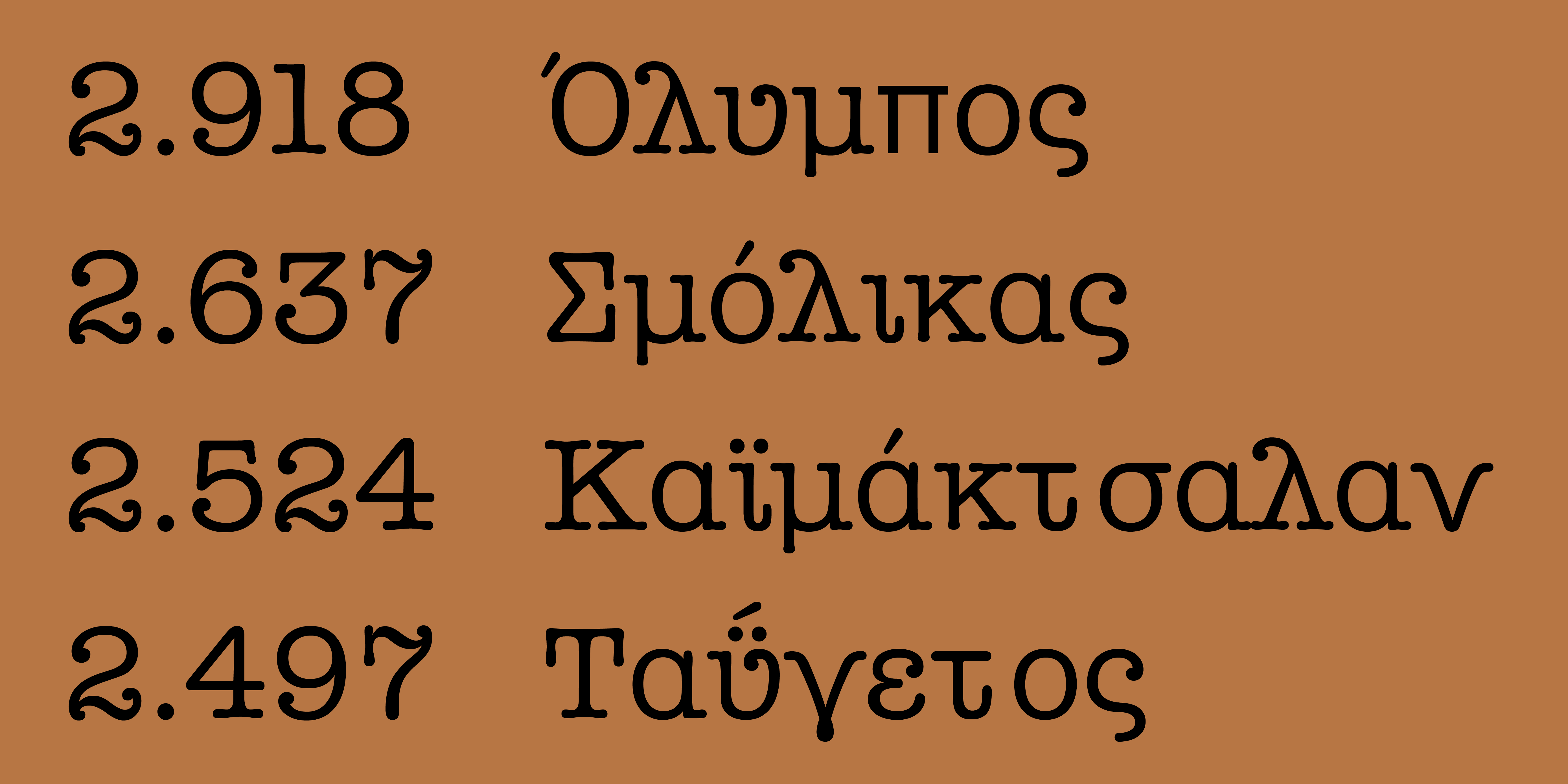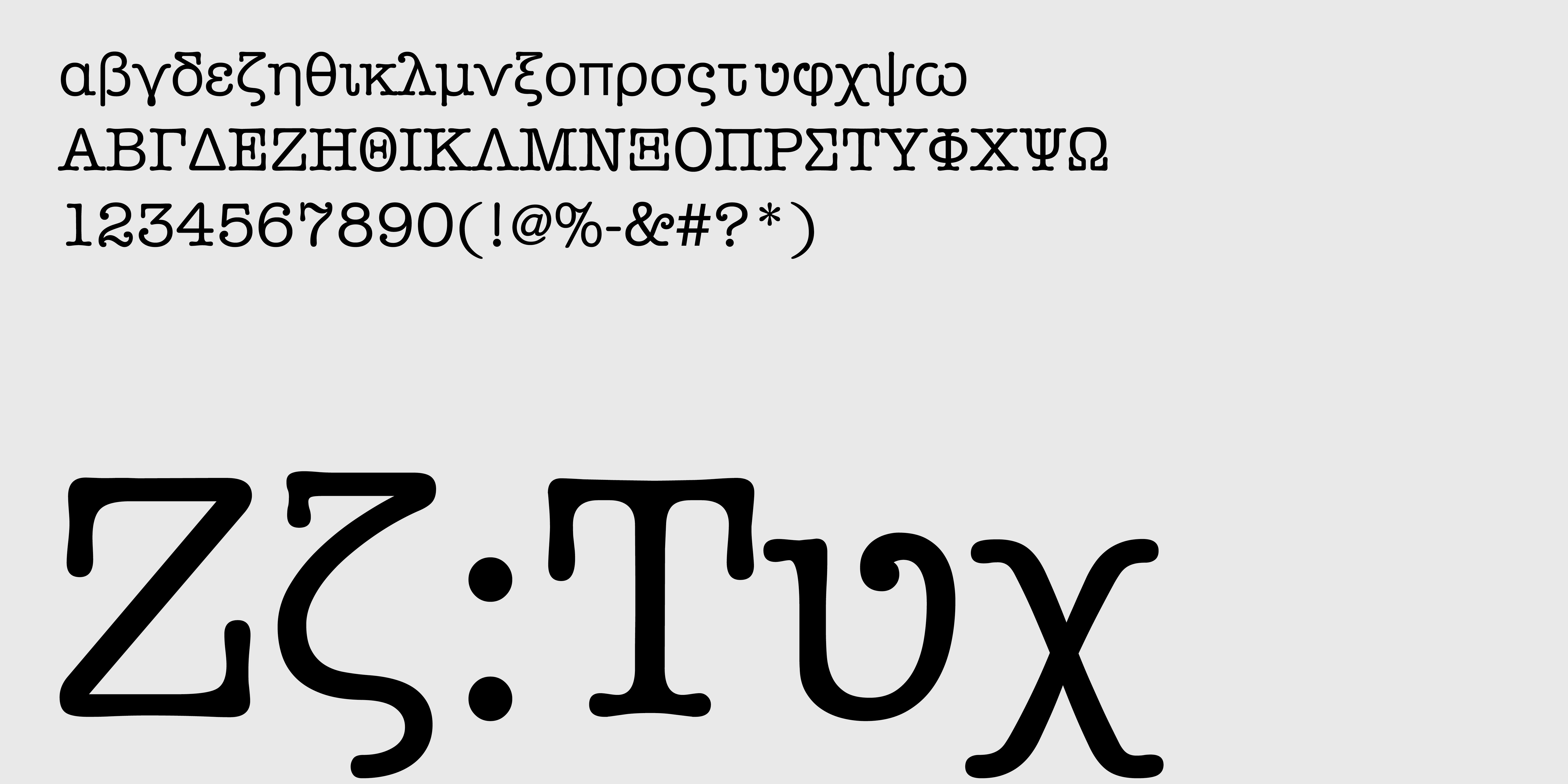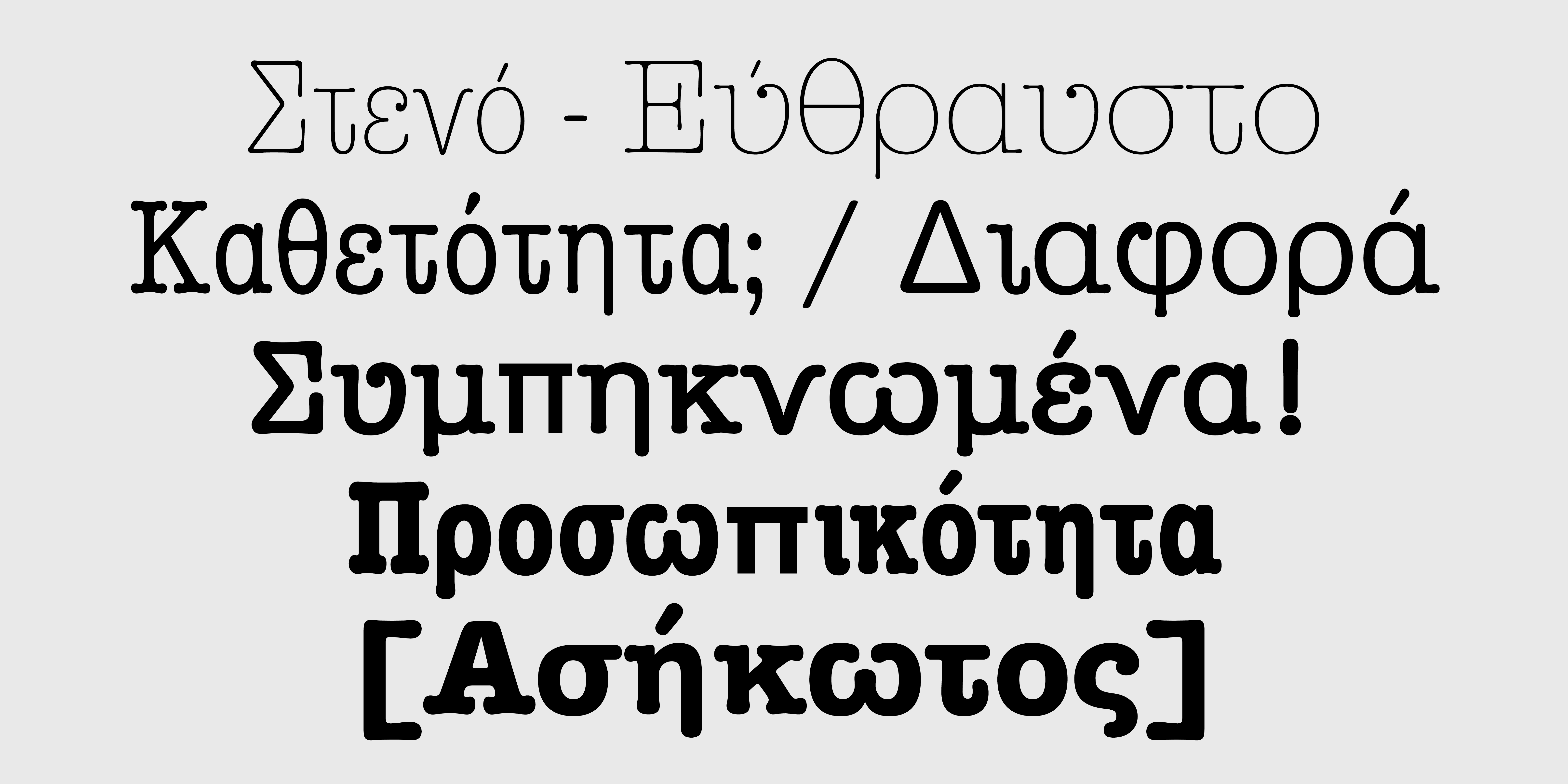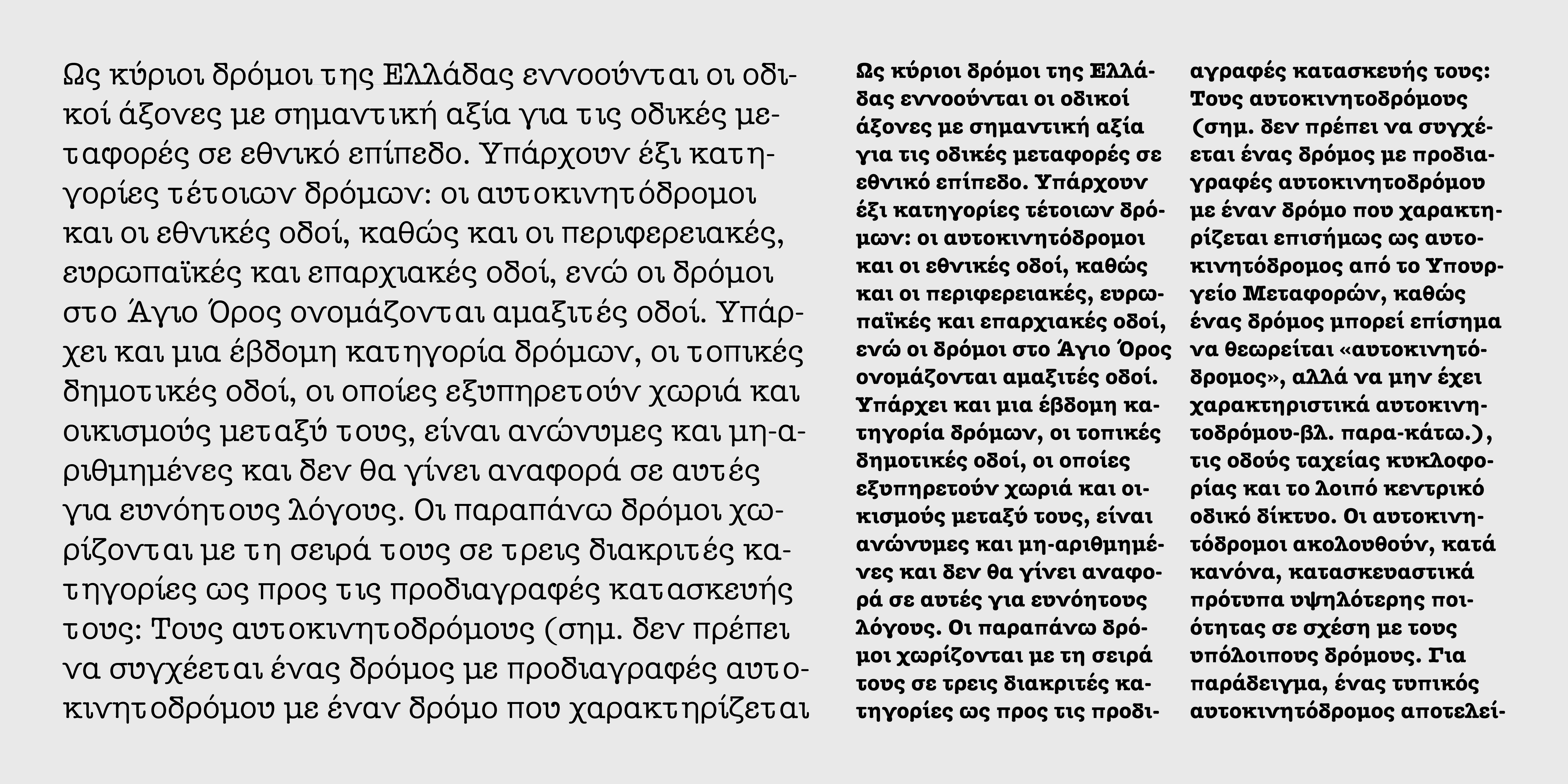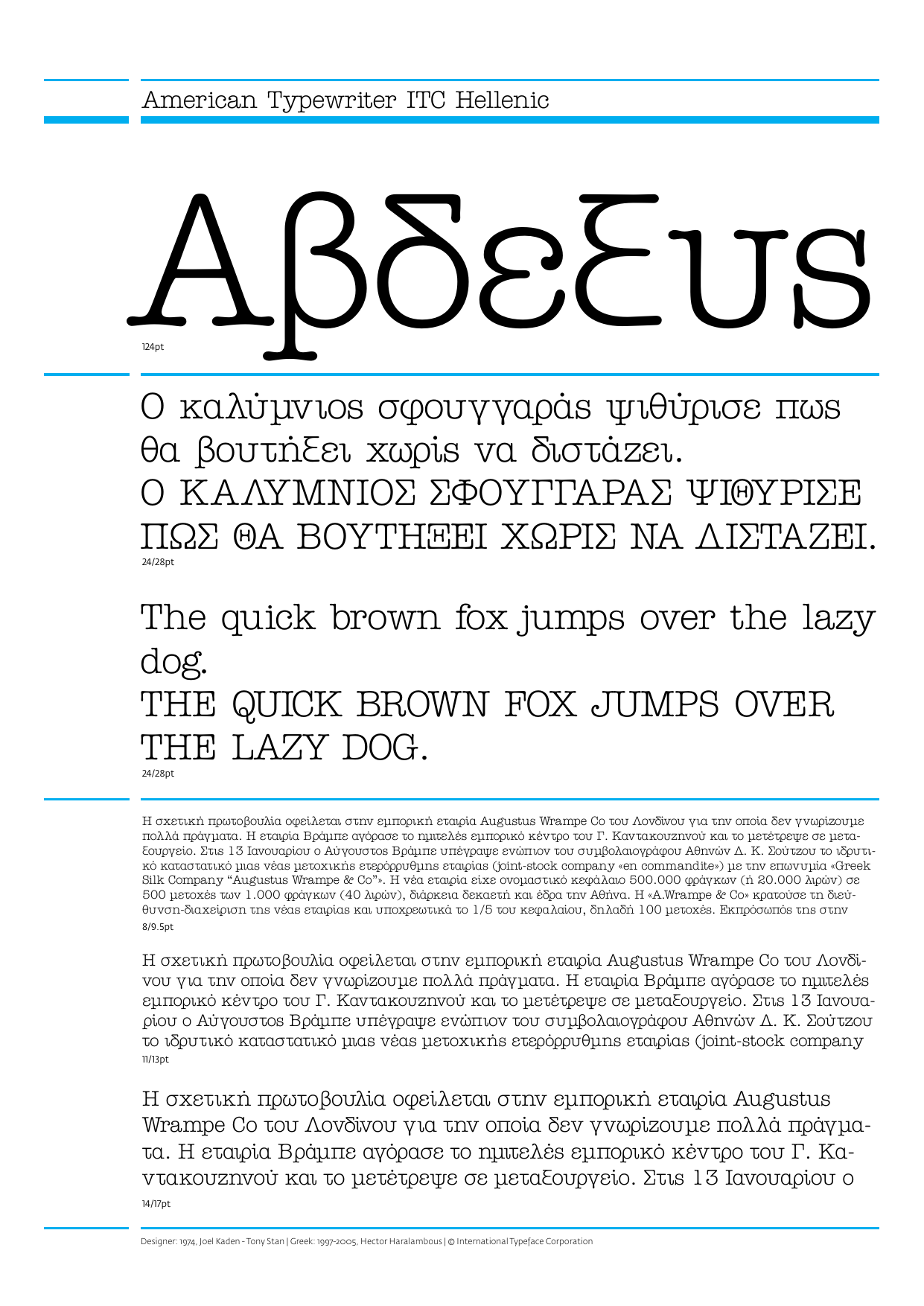
American Typewriter Ελληνικά
Η ITC American Typewriter δημιουργήθηκε από τον Joel Kaden και τον Tony Stan. Είναι μία ωδή στην εφεύρεση που μορφοποίησε τις αναγνωστικές συνήθειες και την έννοια της αναγνωσιμότητας, τη γραφομηχανή. Είναι ένας συμβιβασμός μεταξύ της ακαμψίας του προγόνου της και της προσδοκίας της ψηφιακής εποχής, η ITC American Typewriter διατηρεί την τυπική αλφαβητική φόρμα της γραφομηχανής, δανείζοντας στην γραμματοσειρά έναν υπαινιγμό νοσταλγίας. Η ελληνική έκδοση δανείζεται περισσότερα στοιχεία από τη λατινική παρά από την ελληνική γραφομηχανή.